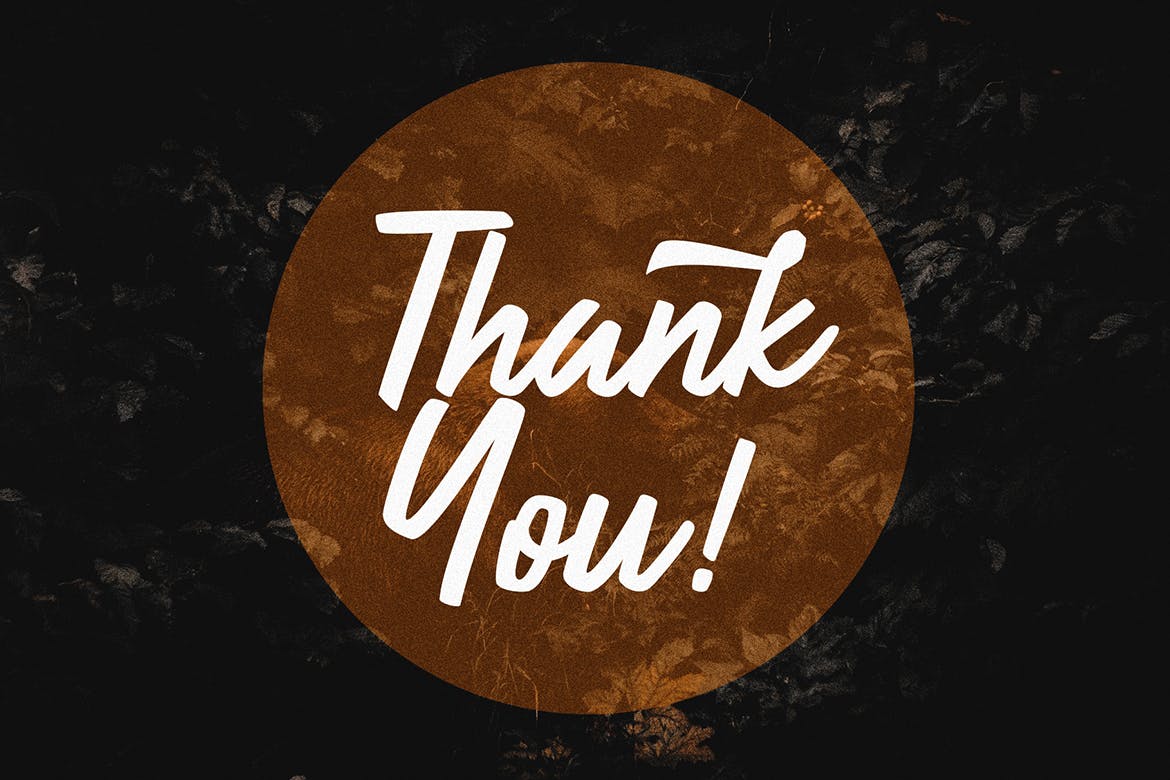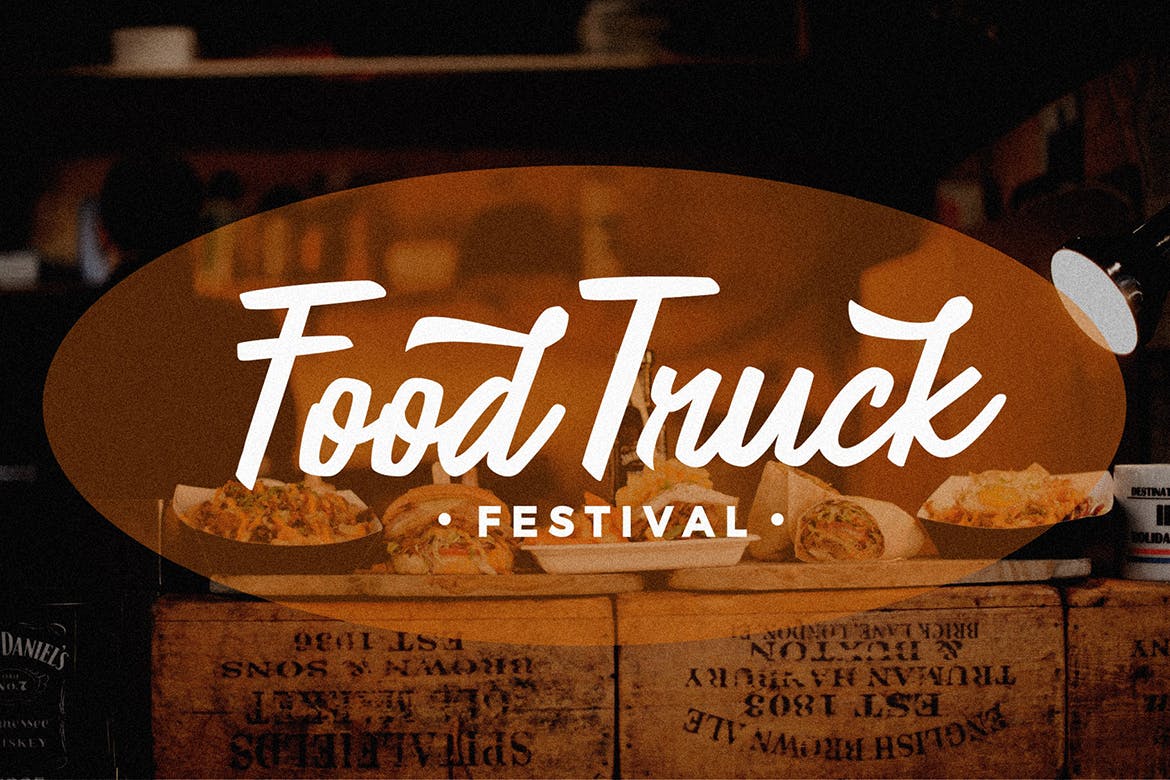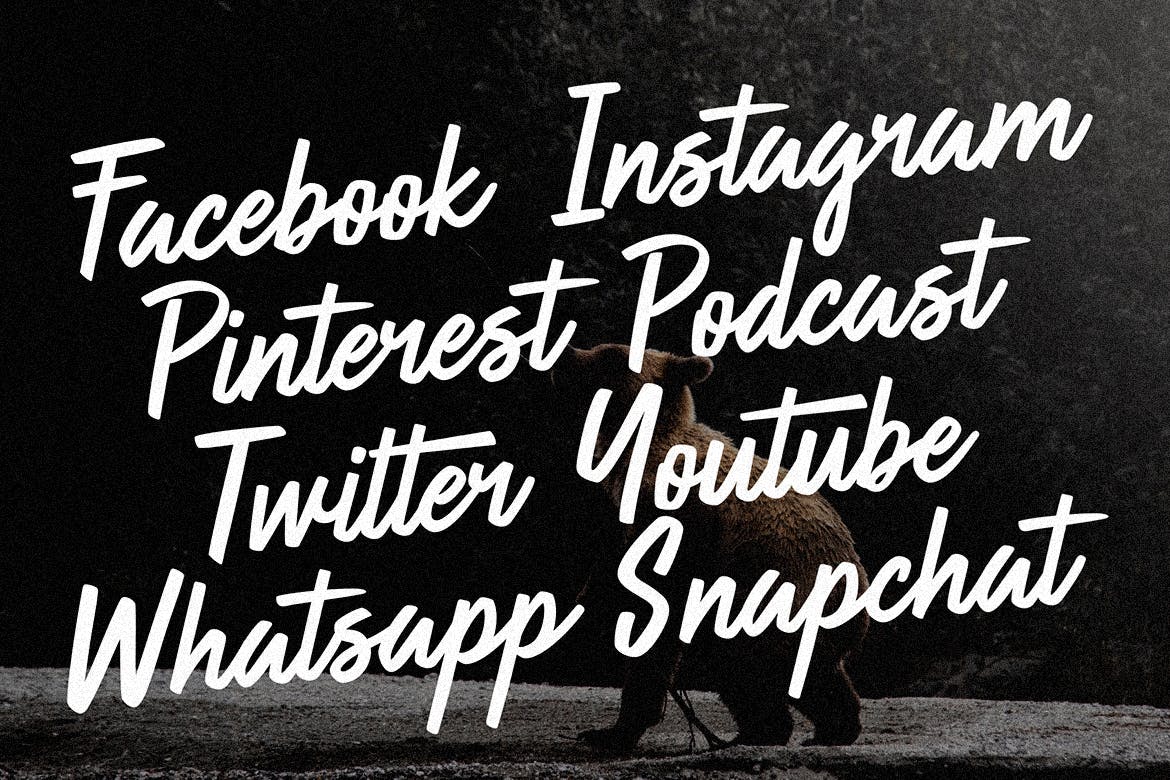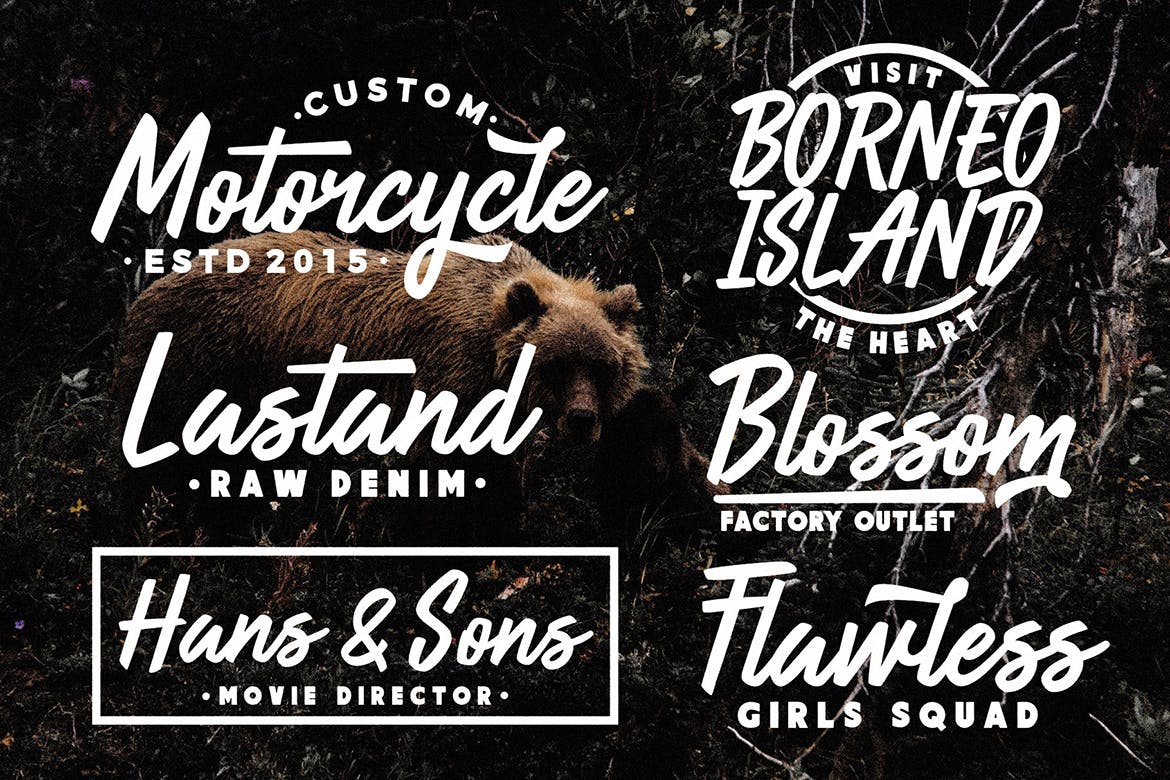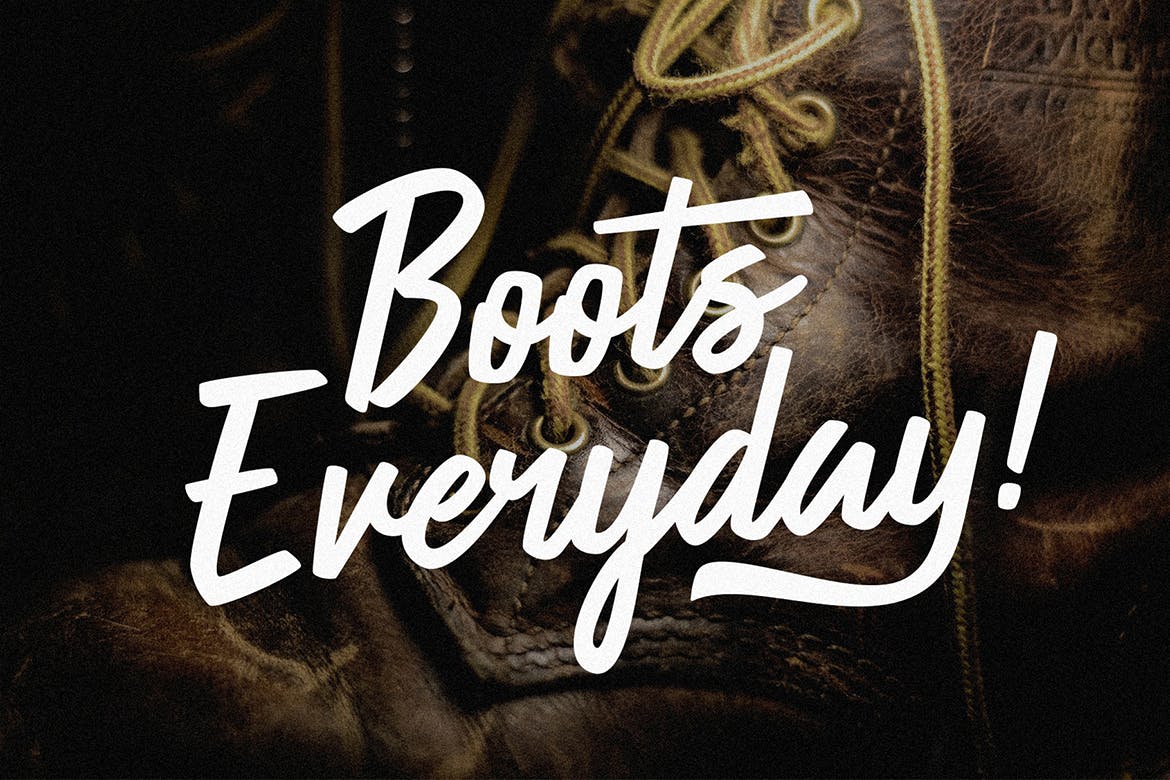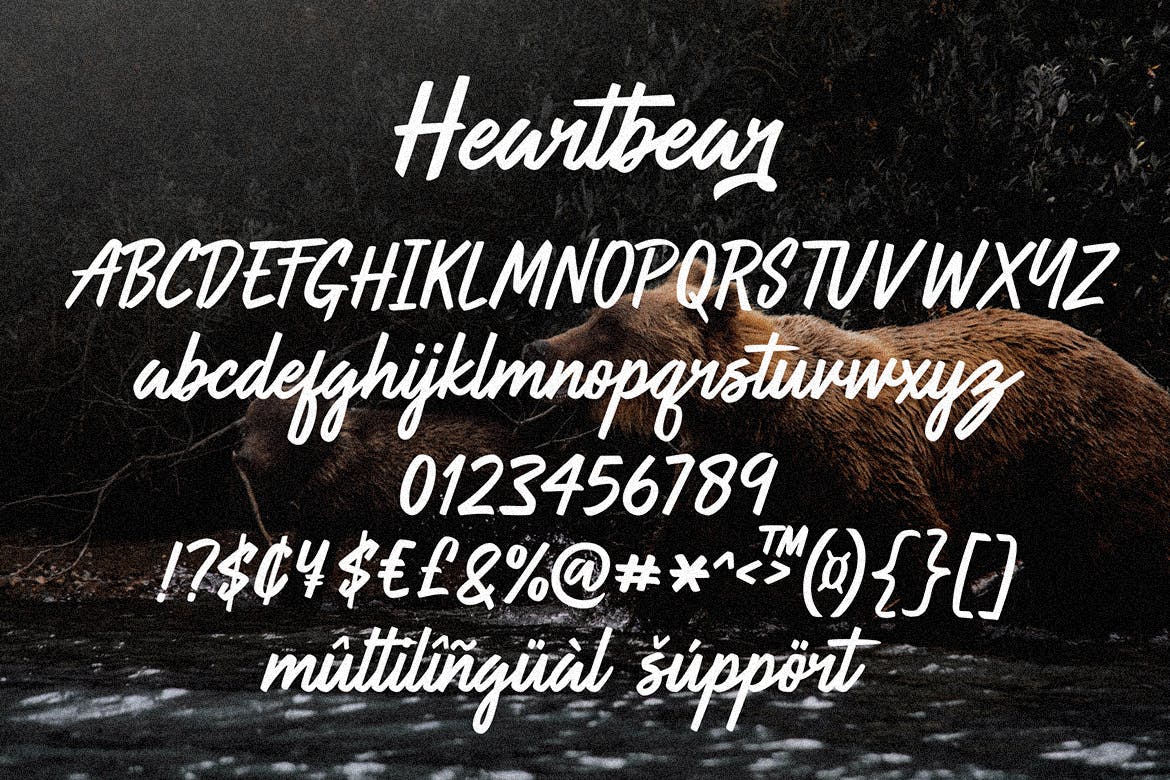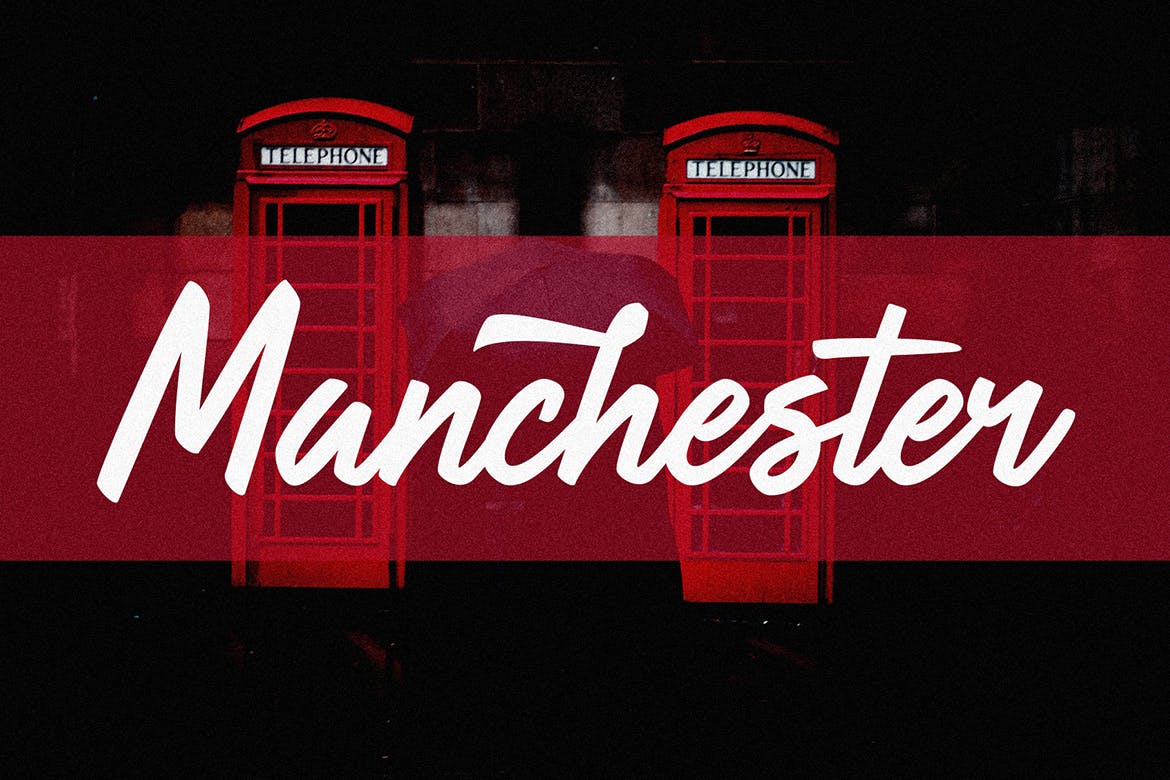
به فونت HEARTBEAT سلام کنید! یک فونت دستنویس ضخیم با سبک ساده و کلاسیک!
این فونت واقعاً برای تمام پروژههای طراحی شما مناسب است، مانند کارت دعوت، لوگوی محصول، نقلقولها، کارت ویزیت، لوگوی برند غذایی و بسیاری موارد دیگر.
فونت Heartbeat با ویژگیهای OpenType مانند مجموعههای استایلیستیک 01 و جایگزینهای استایلیستیک همراه است و از فایلهای فونت کدگذاری شده PUA پشتیبانی میکند تا در نرمافزارهایی که از ویژگیهای OpenType پشتیبانی نمیکنند، مانند Silhouette، Inkscape و غیره، قابل استفاده باشد.